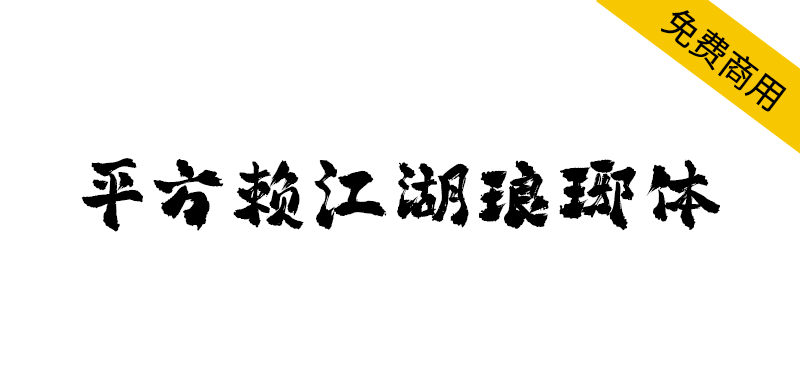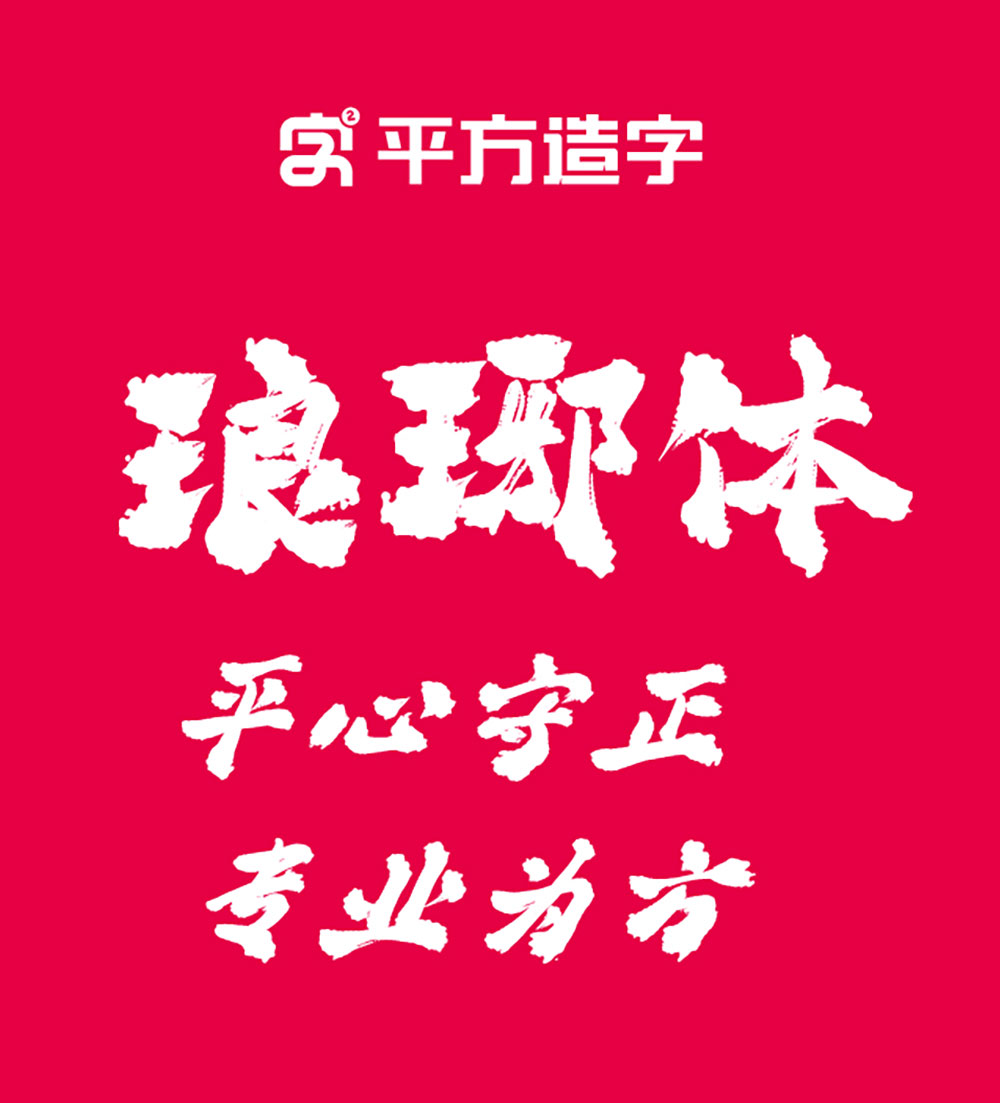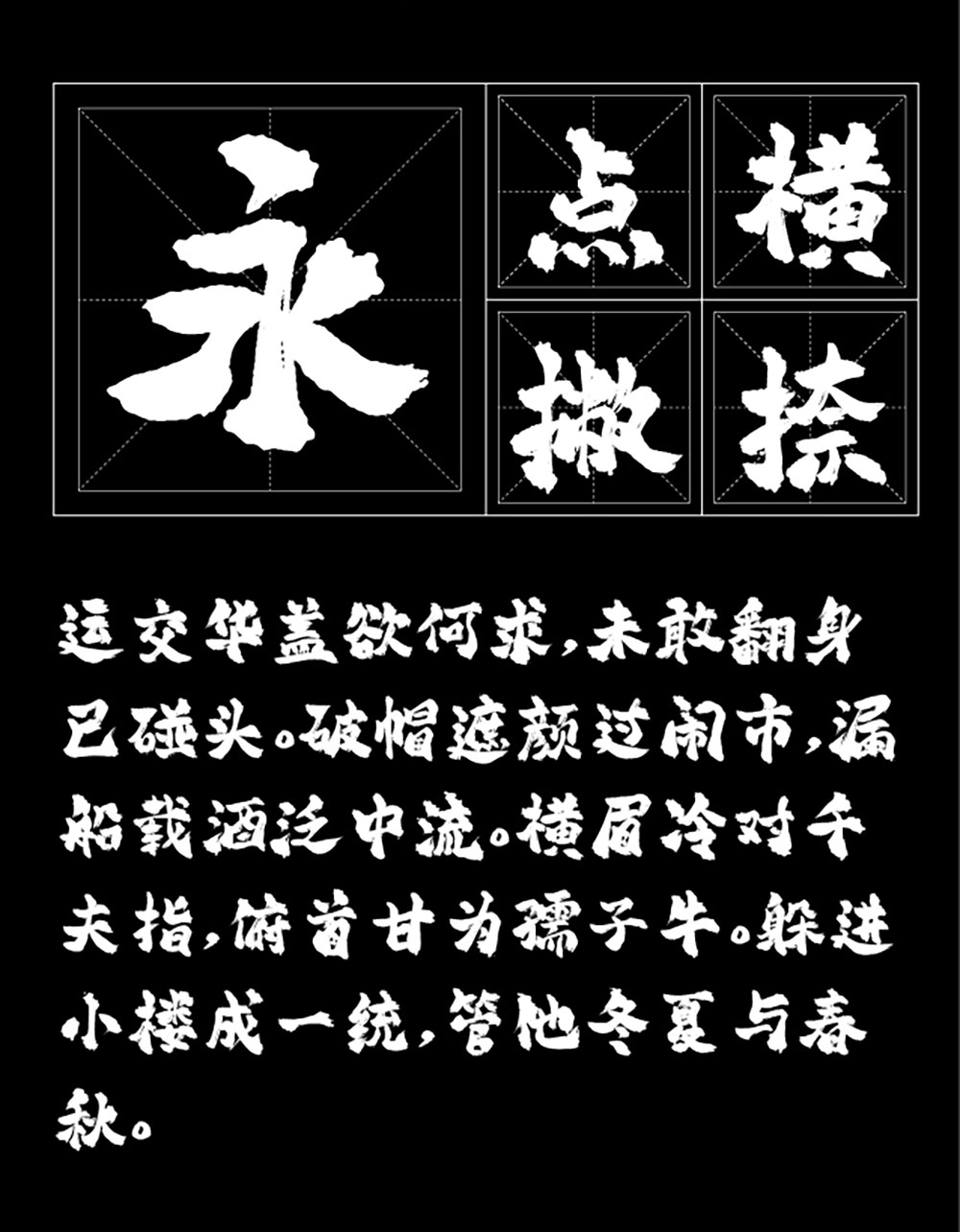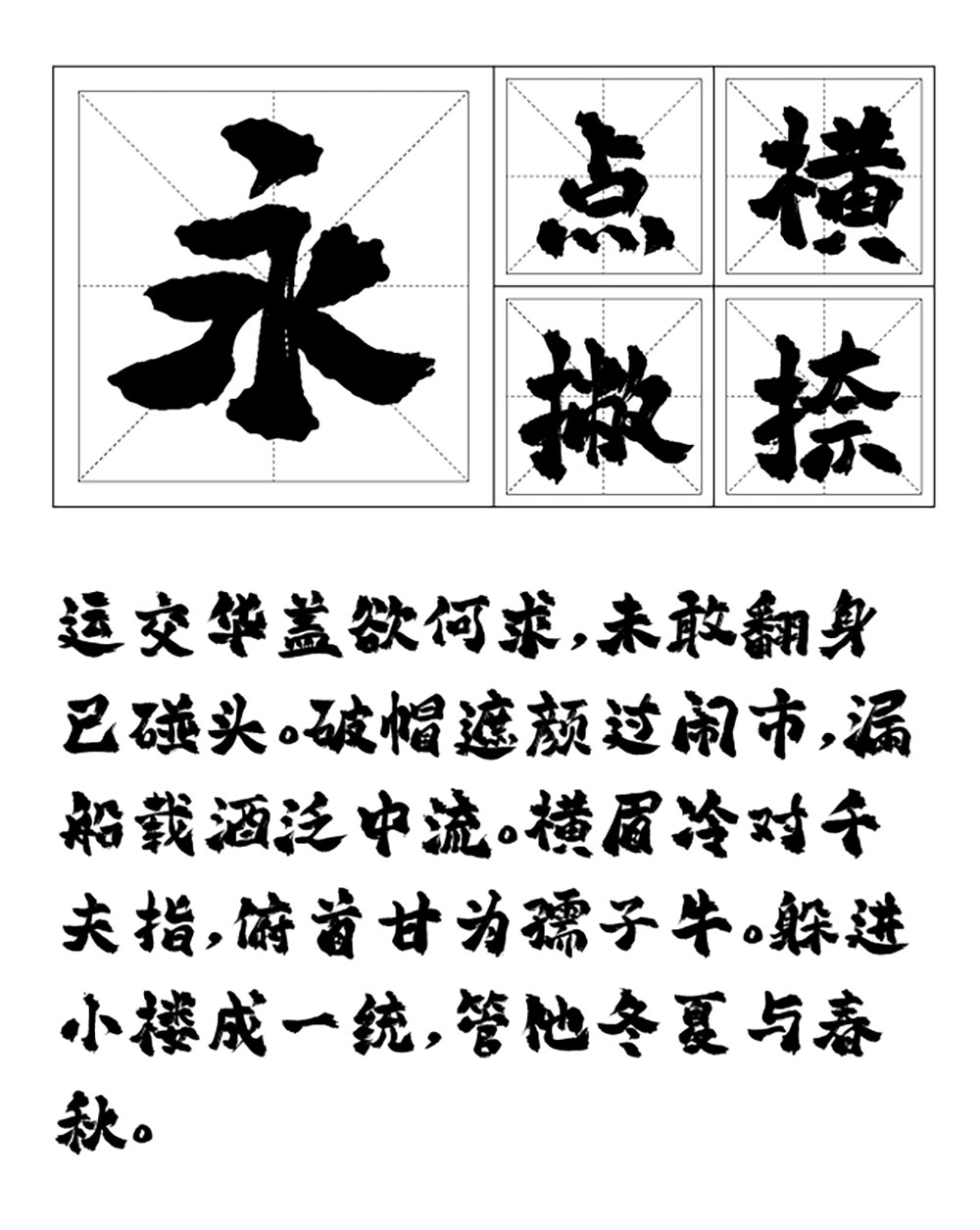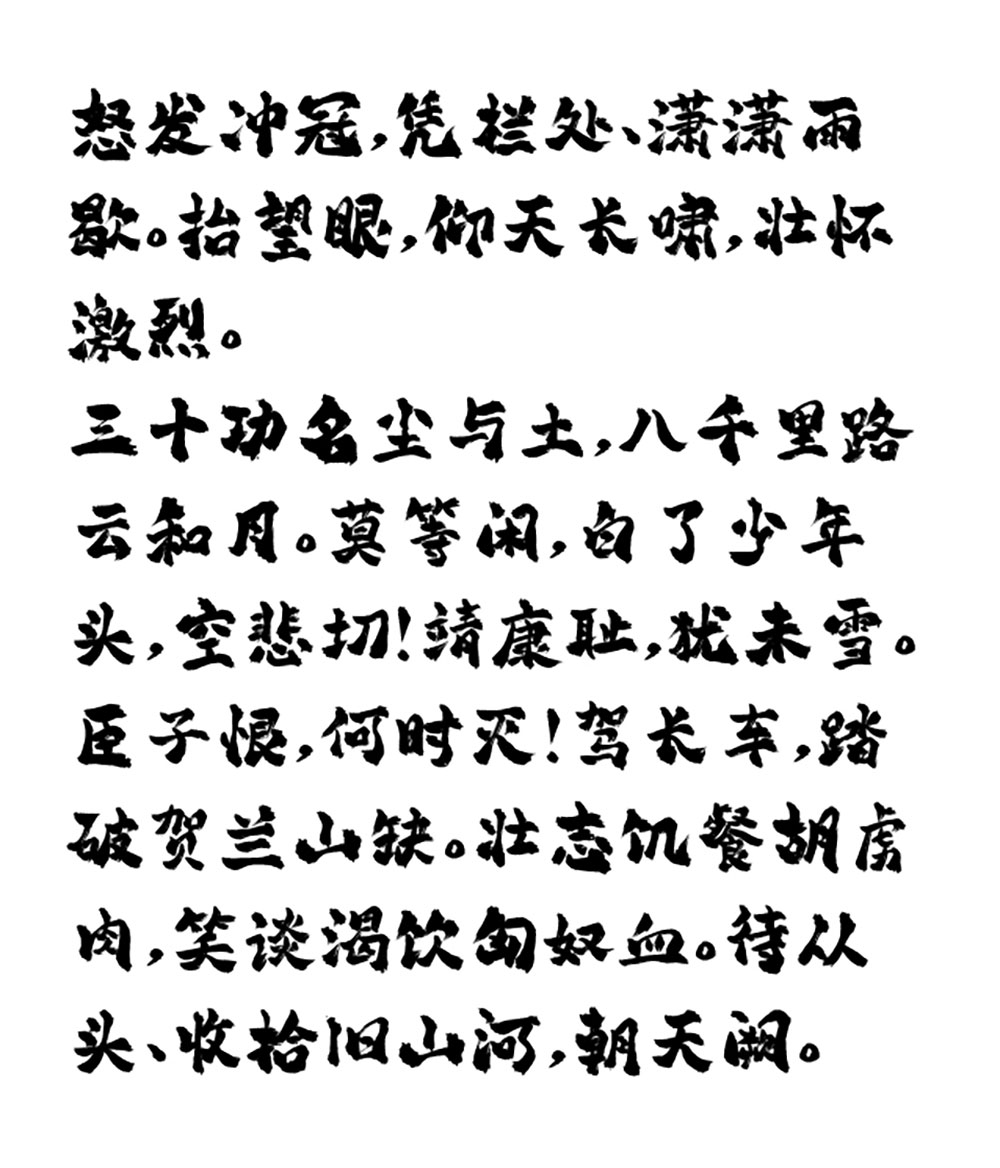
【平方赖江湖琅琊体】一款带有古风气息的毛笔书法字体
还在为设计作品缺乏文化底蕴而烦恼?这款由书法名家赖江湖亲创的毛笔字体,完美复刻宣纸墨韵,连飞白枯笔都纤毫毕现!6763个汉字全收录,商用完全免费且无需授权。即刻解锁这款让设计瞬间拥有千年风骨的秘密武器,你的排版即将告别平庸。
【平方赖江湖琅琊体】一款带有古风气息的毛笔书法字体
平方赖江湖琅琊体是一款具有传统韵味的毛笔书法字体,其设计完美还原了毛笔书写的艺术特征,线条浑厚饱满,笔力雄健挺拔,每个字形都保留了毛笔特有的飞白、枯笔等自然笔触效果,使字体整体呈现出浓郁的书法艺术表现力。